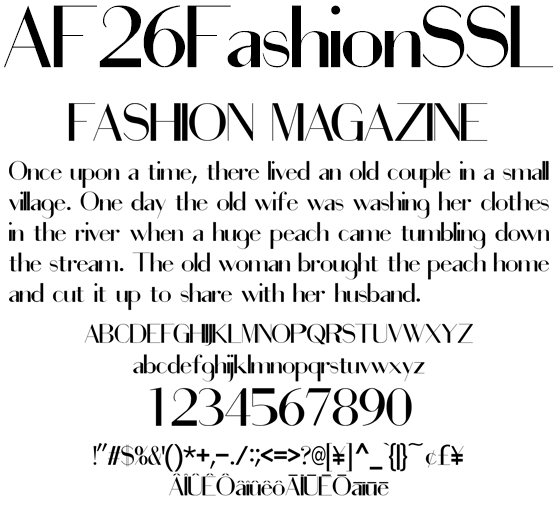
ファッション系 細字サンセリフ欧文 AF26FashionSSL
AF26FashionSSL
モダンフェイスなサンセリフ体。ファッション系のテキストに最適な細字欧文フォントです。ドキュメント、写真、動画テロップ、WebPage にご利用いただける欧文フォントです。日本のローマ字表記で使われる訓令式やヘボン式で扱う Ô や Ō を収録、人名地名へのアプローチもリアルです。